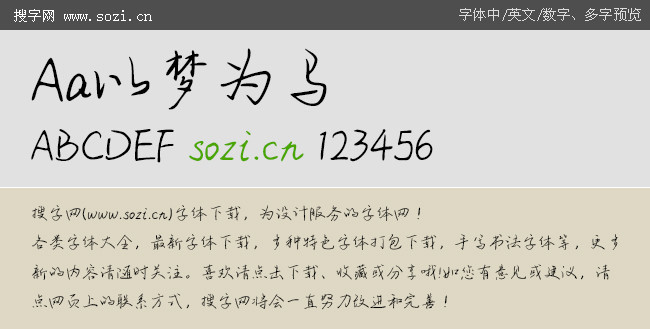
Aa以夢(mèng)為馬(非商業(yè)使用)
搜字網(wǎng)給大家提供一款A(yù)a以夢(mèng)為馬(非商業(yè)使用)中文字體下載,該字體是一款手寫中文字體,這款字體字形瀟灑大方,干凈利落,適合包裝設(shè)計(jì)、書裝設(shè)計(jì)、海報(bào)設(shè)計(jì)等應(yīng)用(此字體為個(gè)人非商用版,商用可以聯(lián)系QQ:1006760504)。